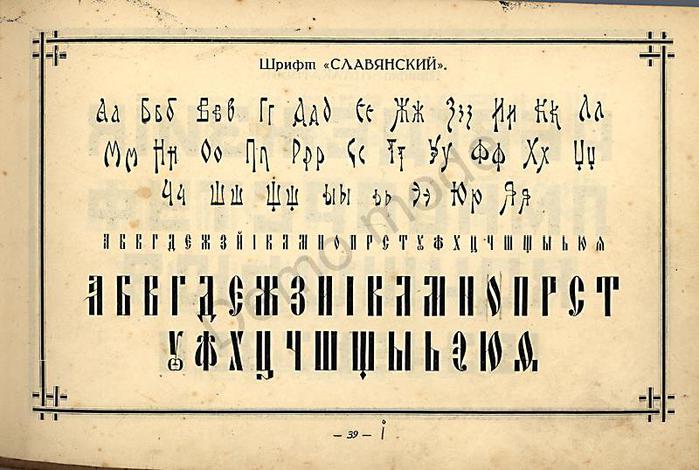
с развитием промышленности и торговли в прошлом веке. Для рекламы по¬
требовались простые, броские и выразительные шрифты.
В России в дореволюционное время типографии пользовались множеством
разнообразнейших, особенно декоративных шрифтов, которые применялись
для украшения книжных переплетов и титульных листов. Часть их из-за ма¬
нерности и вычурности оказалась неприемлемой для нашего времени, хотя
некоторые текстовые типографские шрифты — латинская, обыкновенная, ели¬
заветинская и академическая гарнитуры — широко используются типография¬
ми наравне с новыми, созданными советскими художниками.
В настоящей книге все шрифты сгруппированы в разделы в соответствии
с исторической последовательностью: от старой и новой антиквы до рубленых,
созданных в наши дни.
Первый раздел — текстовые и титульные шрифты, имеющие в своей основе
графические признаки римского капитального шрифта колонны Траяна в Риме.
Шрифты с умеренной контрастностью типа старинной антиквы с острыми
загругляющимися засечками, так называемые медиевальные, а также конт¬
растные, производные от новой, классицистической, антиквы с тонкими
длинными засечками — обыкновенные. Антиквенные расположены не только
в этом разделе, они есть и в разделах декоративных шрифтов. Например,
антиквенный шрифт, выполненный контуром, или орнаментированный, вклю¬
чен в соответствующий раздел контурных или орнаментированных Декора¬
тивных шрифтов. Первый раздел открывается таблицей римского капиталь¬
ного шрифта, который лежит в основе всех современных латинских шрифтов.
Отличаясь простотой форм, он в то же в рюмя является классическим образцом
красоты и торжественности. Древняя антиква в чистом виде может исполь¬
зоваться в надписях особой торжественности и значимости, к примеру, на
дипломах, почетных грамотах, архитектурных сооружениях.
В альбоме много контрастных шрифтов типа новой антиквы, пригодных
ния.
Жирная антиква (английская) хорошо декорируется и трансформи¬руется по начертанию и плотности, а в чистом виде ее чаще применяют в
произведениях русской классической литературы и музыки XIX века.
Второй раздел — шрифты малоконтрастные типа брусковых и египетских
с толстыми прямоугольными засечками и итальянские с очень широкими
горизонтальными засечками. Они несколько тяжеловесны и громоздки, исполь¬
зовать их как текстовые не следует.
Третий раздел — шрифты с едва наметившимися засечками, переходные
от шрифтов с засечками к рубленым (гротесковым) без засечек и шрифты
типа ленточной антиквы, контрастные без засечек. Очень близкие к древней
антикве ленточные шрифты могут быть использованы как заголовочные и
текстовые, потому что они не обременены особыми декоративными элементами.
пропорций, сделать оттененными, объемными или контурными.
Четвертый раздел — шрифты рубленые (гротесковые) без засечек, не¬
контрастные.
Найдут широкое применение в плакатах, рекламе, при написании
лозунгов, призывов. Эти шрифты хорошо читаются на расстоянии. Они также
могут быть декоративными, если их выполнить в цвете, контуром или сделать
оттененными.
Пятый раздел — рукописные, каллиграфические и свободно написанные
кистью, а также шрифты, имеющие сходство с рукописными. Декоративно
выглядит надпись на почетной грамоте или дипломе, на пригласительном
билете или визитной карточке, текст поздравительного адреса, выполненный
каллиграфическим шрифтом.
Шестой раздел — контурные, оттененные и объемные декоративные шриф¬
Контурность делает их легкими при различных размерах, и надпись, выпол¬
ненная таким шрифтом, может хорошо сочетаться с наборным текстом и
украшать его. Найдут применение и другие шрифты этого раздела в наглядной
агитации, рекламе, афишах, плакатах.
Седьмой раздел — так называемые национальные шрифты: старинный
русский, украинский, грузинский, армянский, индийский, арабский, китайский
(вернее, имитация этих шрифтов).
Эти шрифты, конечно, лучше использовать
для надписей на ту или иную национальную тему. Например, для рекламы
индийского фильма правильно будет использовать имитацию индийского
национального шрифта. Готический шрифт лучше применять как декоратив¬
ный для написания текста об истории Германии. Но при этом нельзя забывать,
долгое время был национальным шрифтом враждебной нам фашистской
Германии.
Восьмой раздел — декоративные, орнаментированные, старые и новые, на
русской и латинской основе шрифты. Их можно широко использовать для
оформления всякого рода этикеток, упаковки и художественной литературы.
Девятый раздел — шрифты для художественного оформления книг:
инициалы рукописных и печатных книг, титульные листы и переплеты,
отдельные художественные надписи. Они собраны здесь в качестве примеров
декоративного оформления инициалов-буквиц в книге, поздравительном адре¬